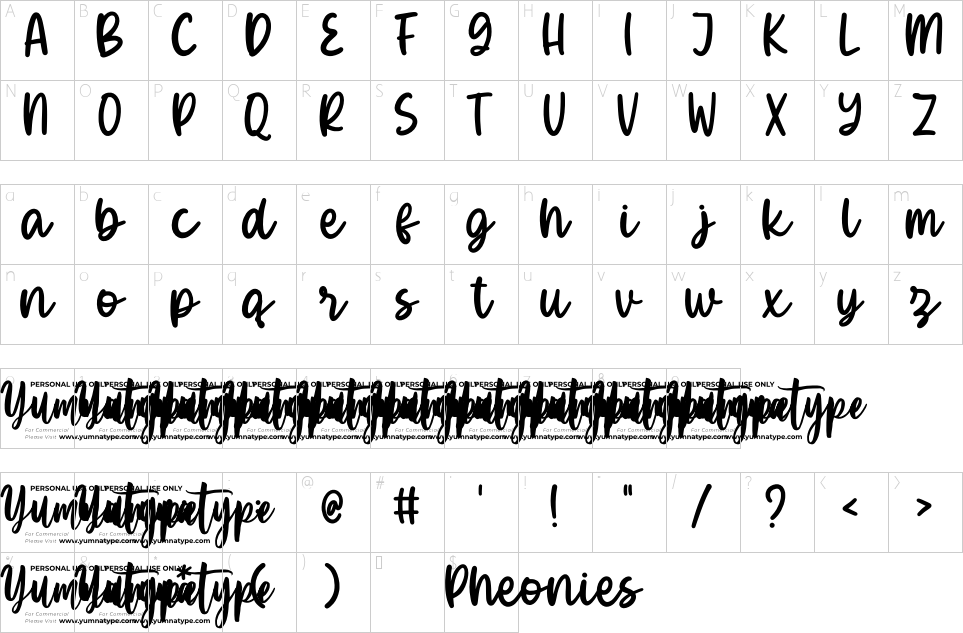
Descubra a elegância da Pheonies Font, uma opção gratuita para designers do Brasil que valorizam estilo moderno em suas criações digitais. Desenvolvida pela Yumna Type, essa fonte foi projetada pensando nas demandas e preferências brasileiras, oferecendo um equilíbrio perfeito entre simplicidade e elegância. Com seu design minimalista, a Pheonies se destaca por ser fácil de ler em diferentes tamanhos e formatos, tornando-a ideal para uso no dia a dia das empresas ou até mesmo na personalização de materiais educacionais. Sua versão gratuita é uma excelente alternativa aos preços mais elevados encontrados com fontes premium, proporcionando ao designer brasileiro acesso a uma qualidade superior sem comprometer o seu orçamento. Com o download da Pheonies Font, você terá um recurso valioso para criar designs personalizados e atemporais que refletem sua identidade visual única.